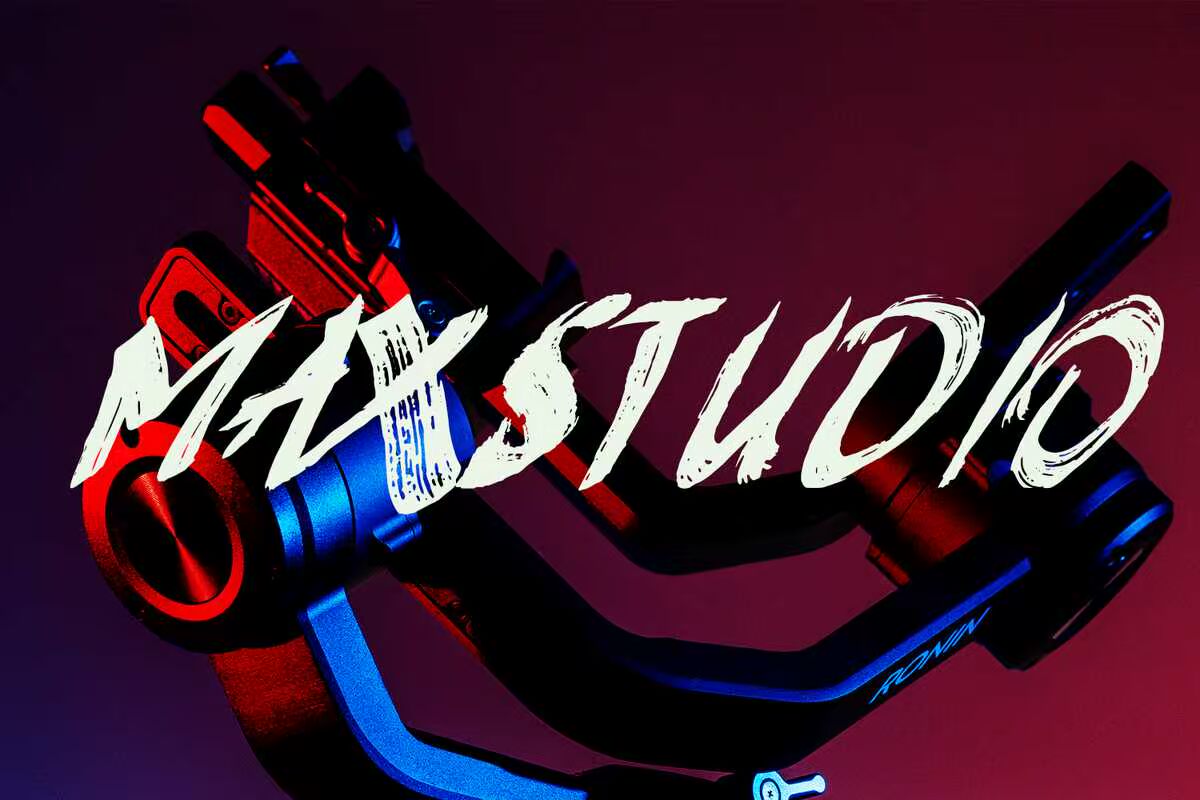
来自Mhdafifersya的TormantedBrushFont将TractiveCurves与新的Hurbanedge相结合;交付一份能保证您的标志设计、品牌形象、手写报价、产品包装、商品、社交媒体或网站字体等吸引眼球的文字说明。来自MHDAFFERSYA的TormantedBrushFont将实用程序与全新的ShurbanEdge相结合;交付保证负载的手写文字,这些文字在您的标志设计、品牌形象、手写报价、产品包装、商品、社交媒体或网站字体上引人注目。